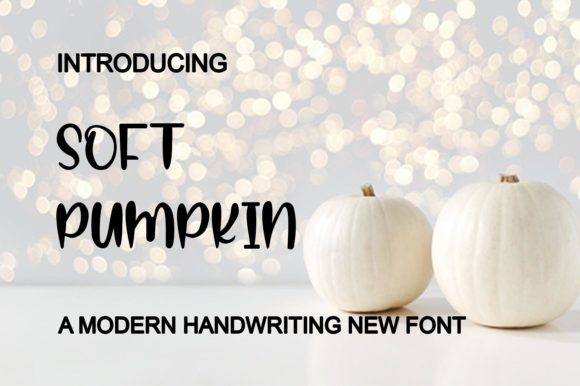
Soft Pumpkin
Soft Pumpkin Font – Avis détaillé et recommandations SEO
La Soft Pumpkin Font est une police d’affichage mignonne et décontractée qui séduit immédiatement par son charme ludique et sa lisibilité impeccable. Que vous travailliez sur des publications Instagram, des scripts de calligraphie pour des projets DIY, ou encore sur des éléments de branding tels que logos, titres, t‑shirts, papier à en‑tête, panneaux, étiquettes, affiches ou badges, cette typographie transforme chaque idée créative en véritable œuvre d’art.
Grâce à ses formes arrondies et à son style chaleureux, la Soft Pumpkin Font attire l’œil tout en restant extrêmement lisible, ce qui en fait un choix idéal pour les contenus destinés aux réseaux sociaux, aux supports imprimés et même aux designs web. Son caractère polyvalent permet de l’utiliser dans divers contextes sans perdre de son impact visuel.
- Logos et identités de marque
- Titres et sous‑titres percutants
- Design de t‑shirts et vêtements personnalisés
- Papier à en‑tête et correspondance professionnelle
- Signalétique intérieure et extérieure
- Étiquettes produit et packaging
- Affiches, flyers et posters promotionnels
- Badges, stickers et éléments de gamification
- Contenus pour Instagram, stories et reels
- Projets de calligraphie DIY et scrapbooking